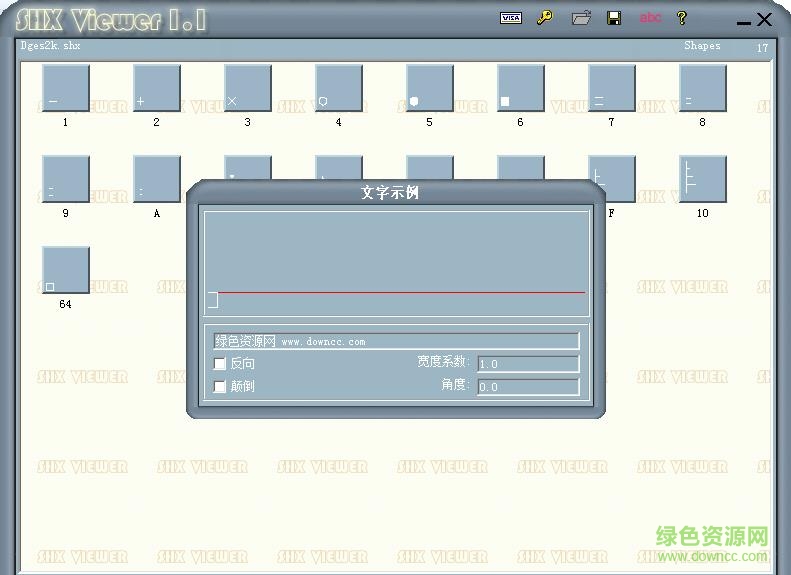
dges2k.shx字體是一款字形字體,讓你能夠在圖紙制作過程中打出專業(yè)的圖紙符號(hào),它不支持文字輸入,同時(shí)使用這款字形文件將能夠快速的打開擁有此字形制作的圖紙,快來綠色資源網(wǎng)下載吧!
dges2k.shx字體小編點(diǎn)評(píng)
dges2k.shx字形在cad軟件中存儲(chǔ)在font文件夾下,當(dāng)用戶需要輸入此內(nèi)的各類符號(hào)時(shí)就能夠進(jìn)行調(diào)用,讓你能夠正常的成功的輸入制圖符號(hào)!
dges2k.shx字體
dges2k.shx字體介紹